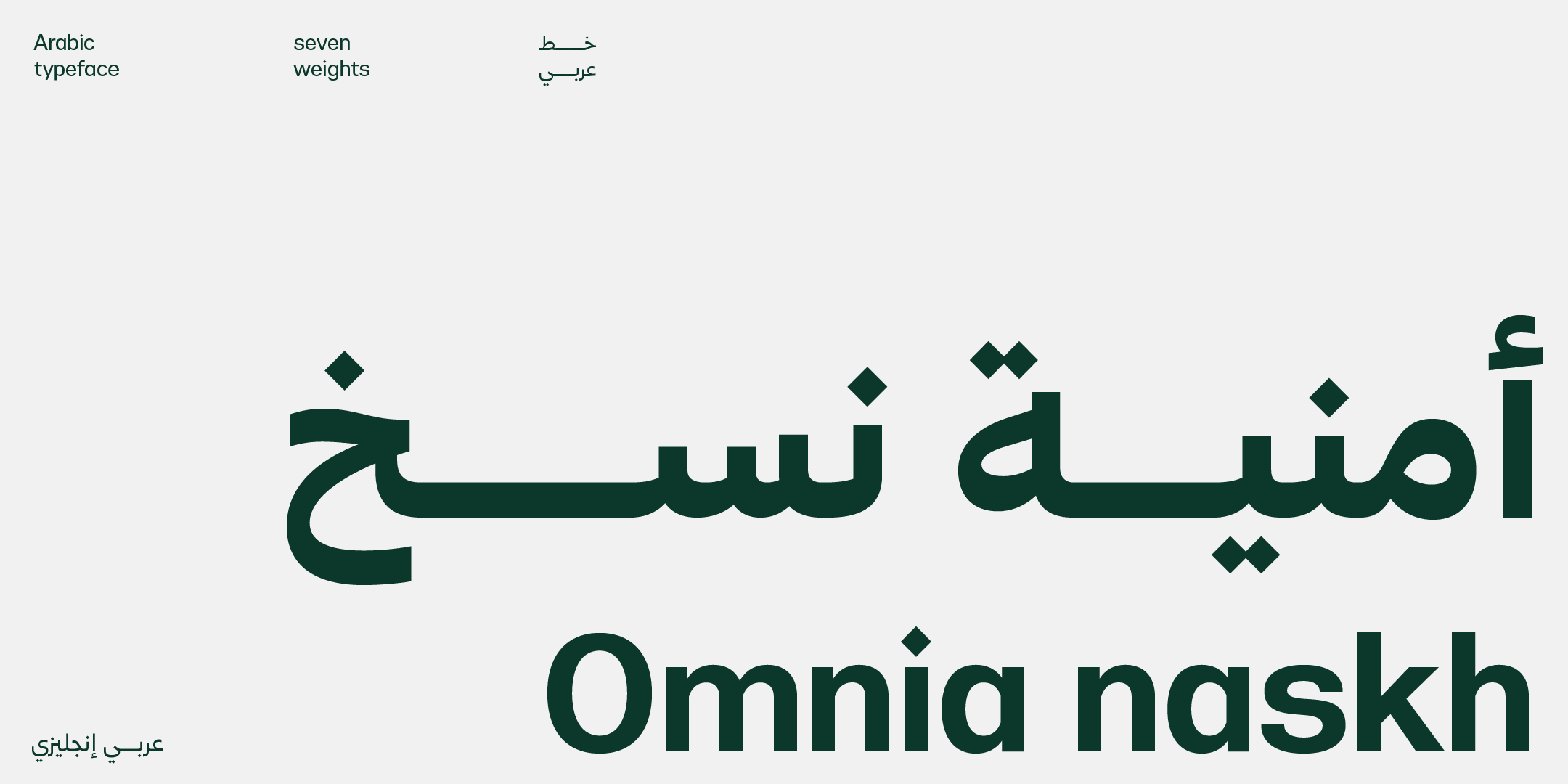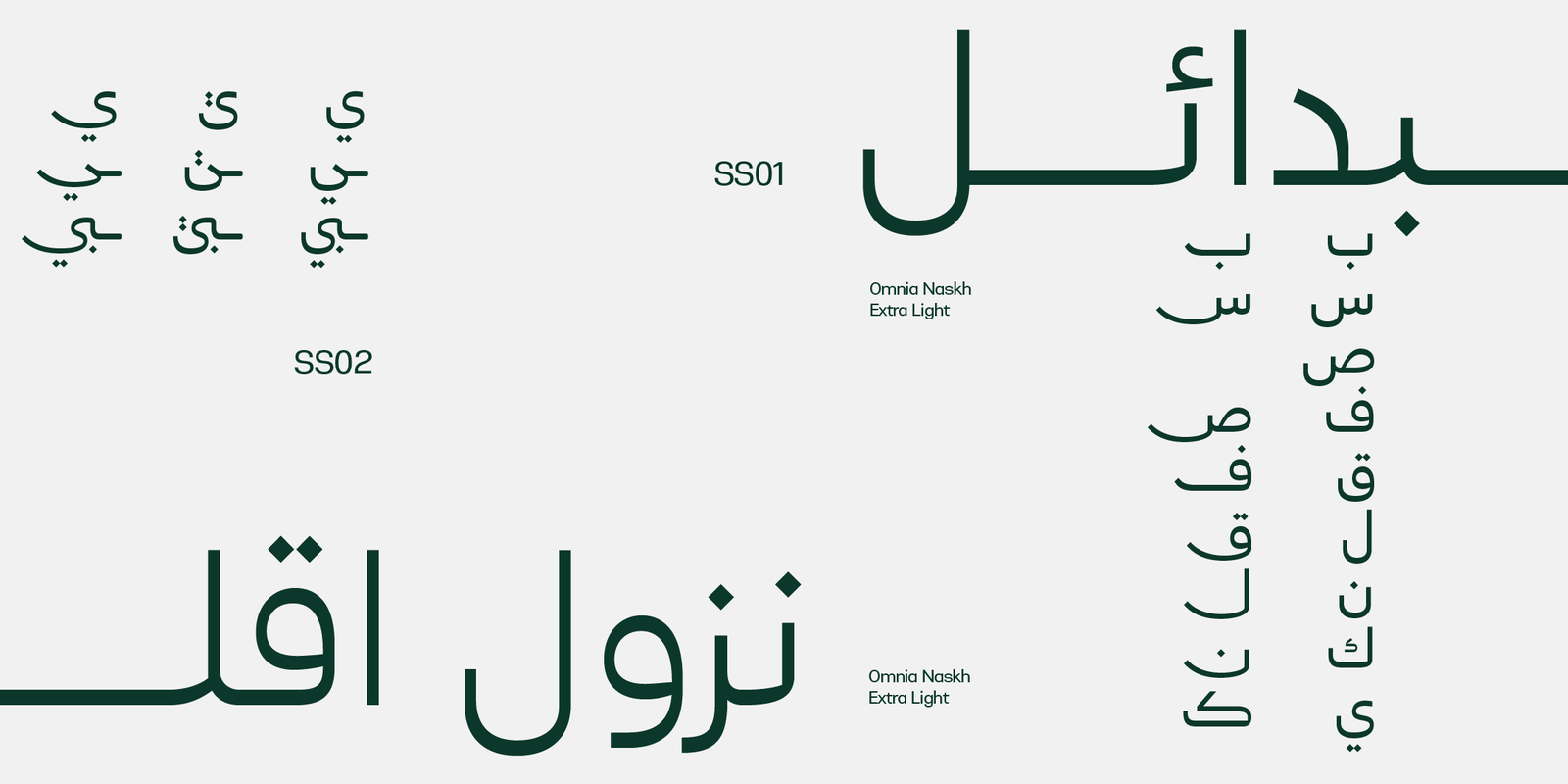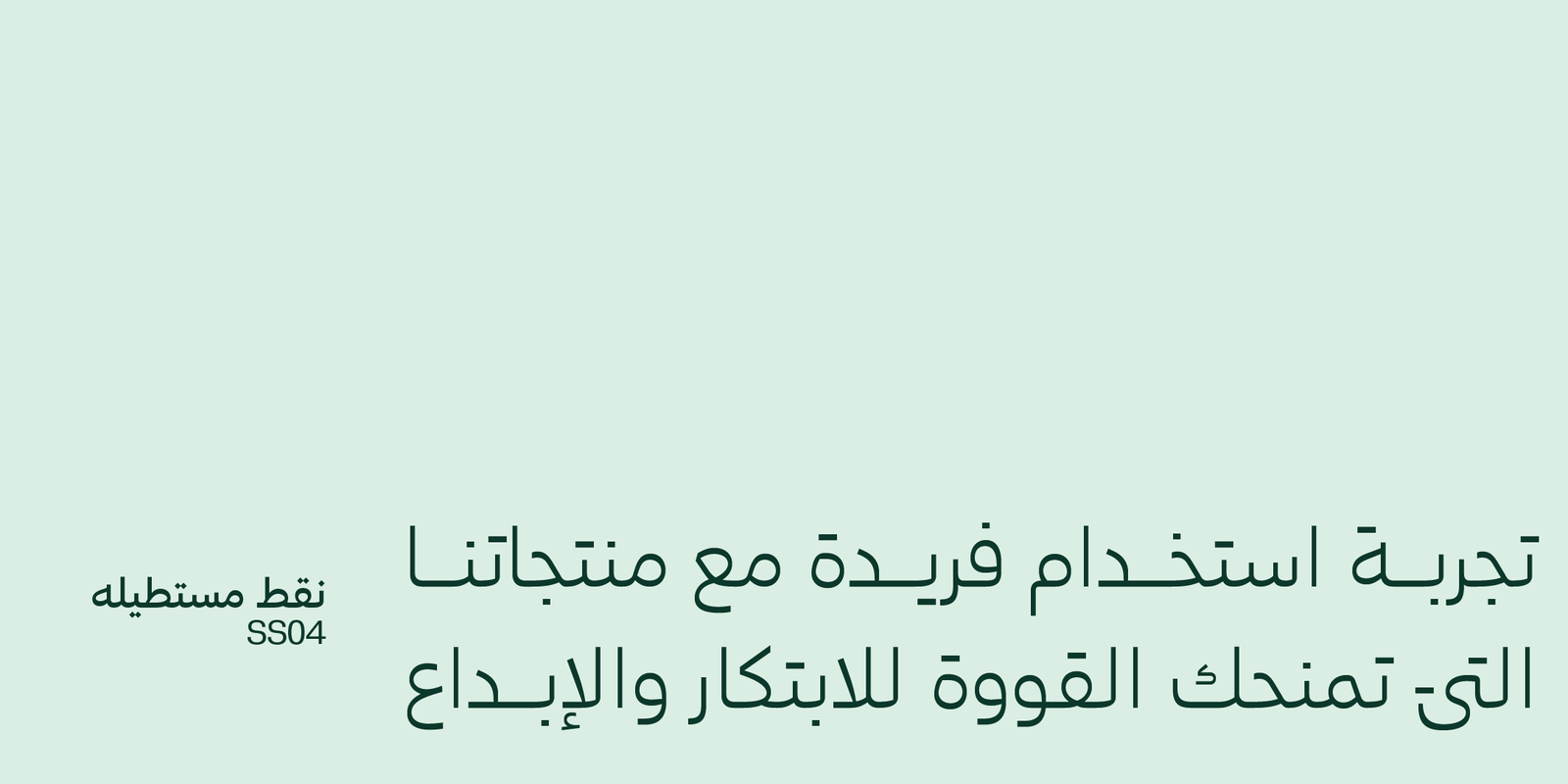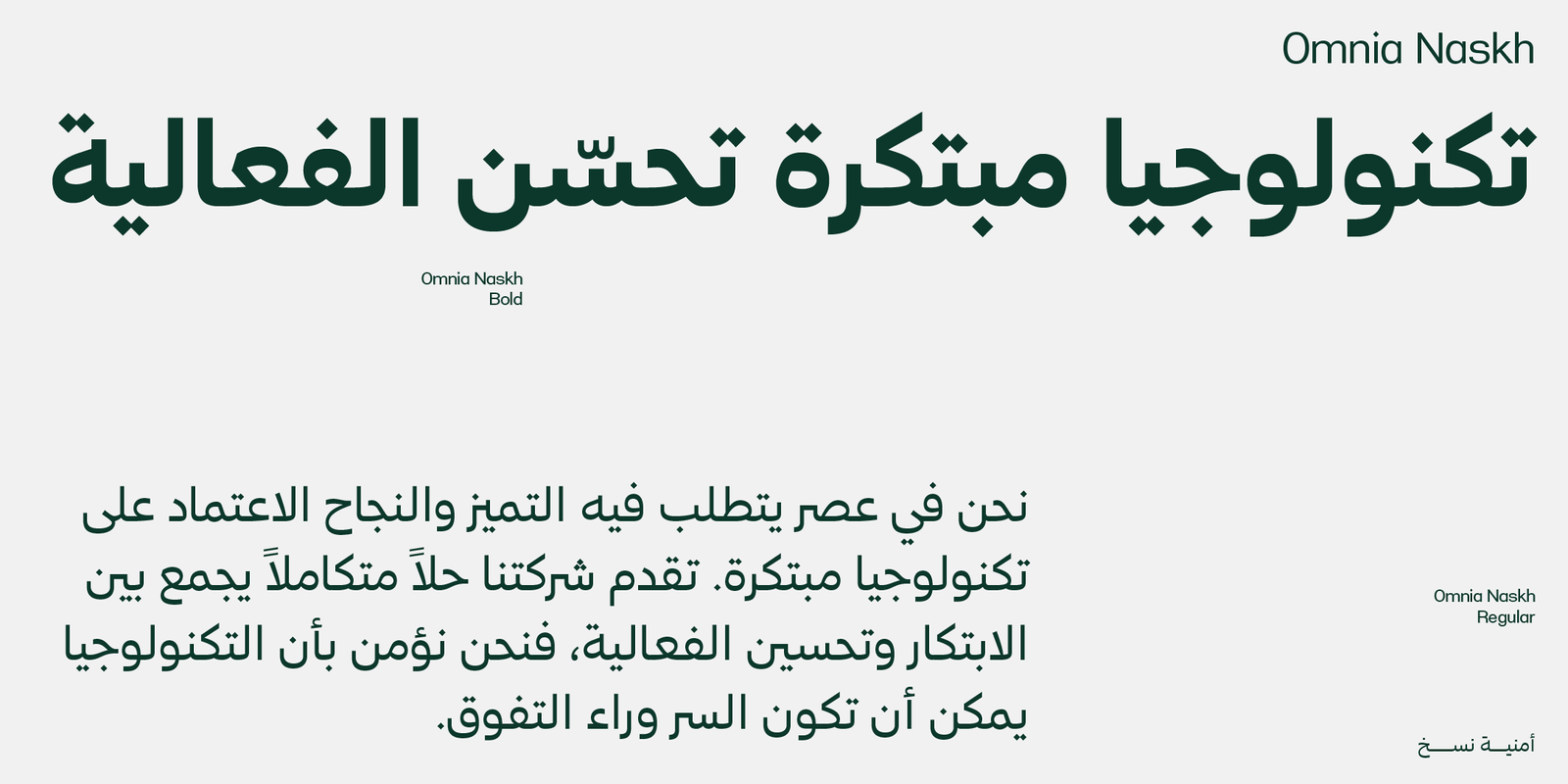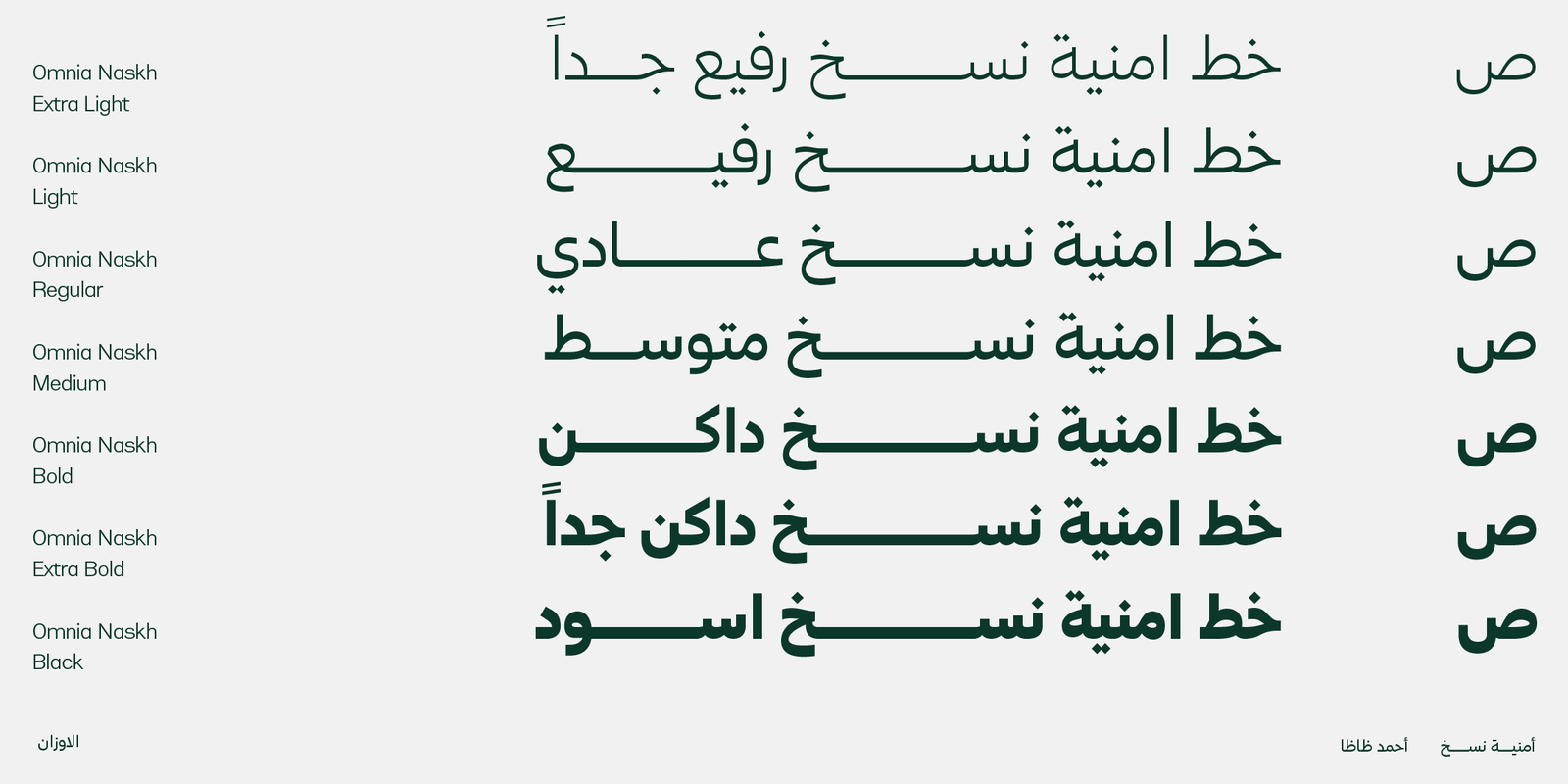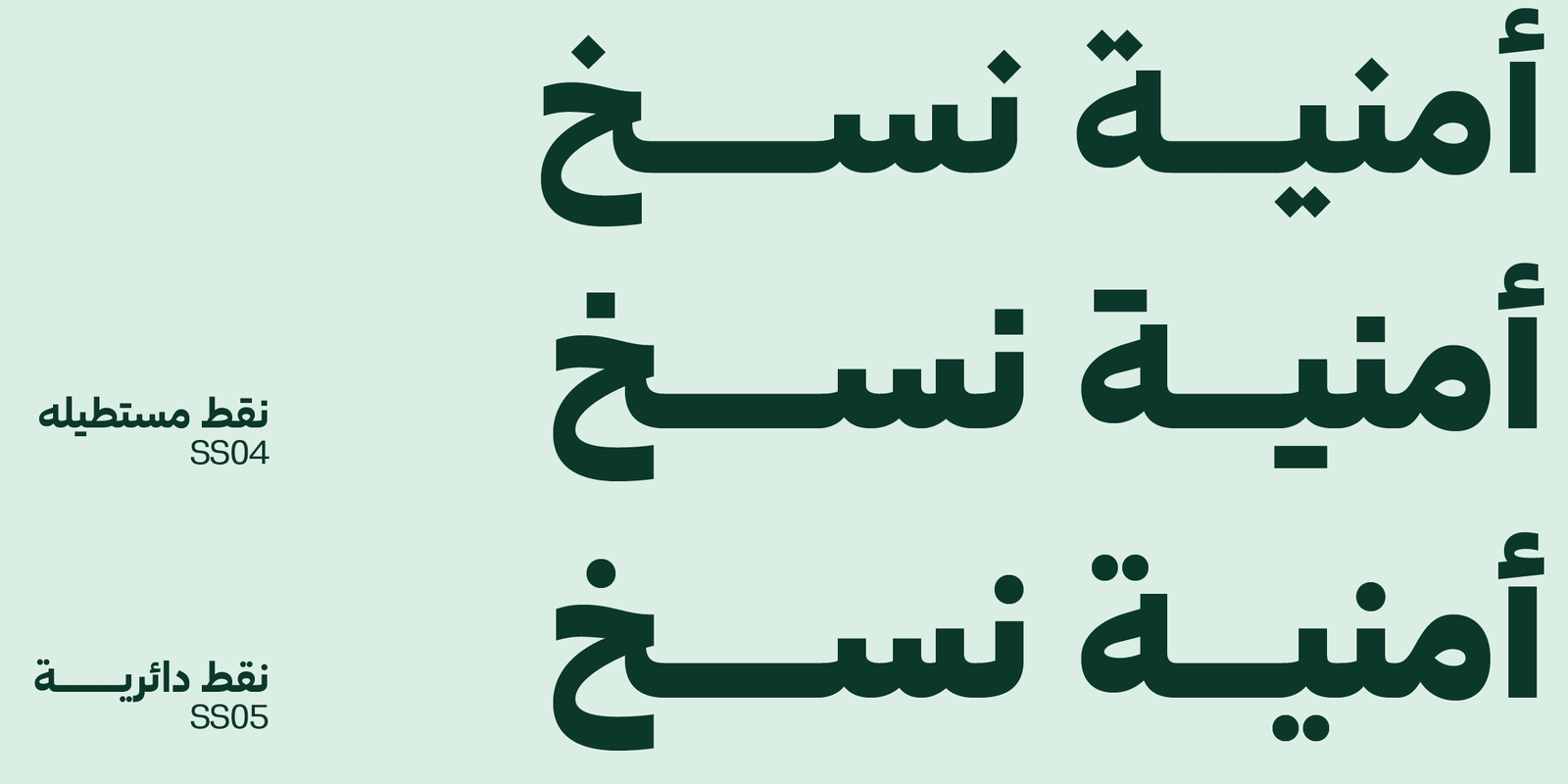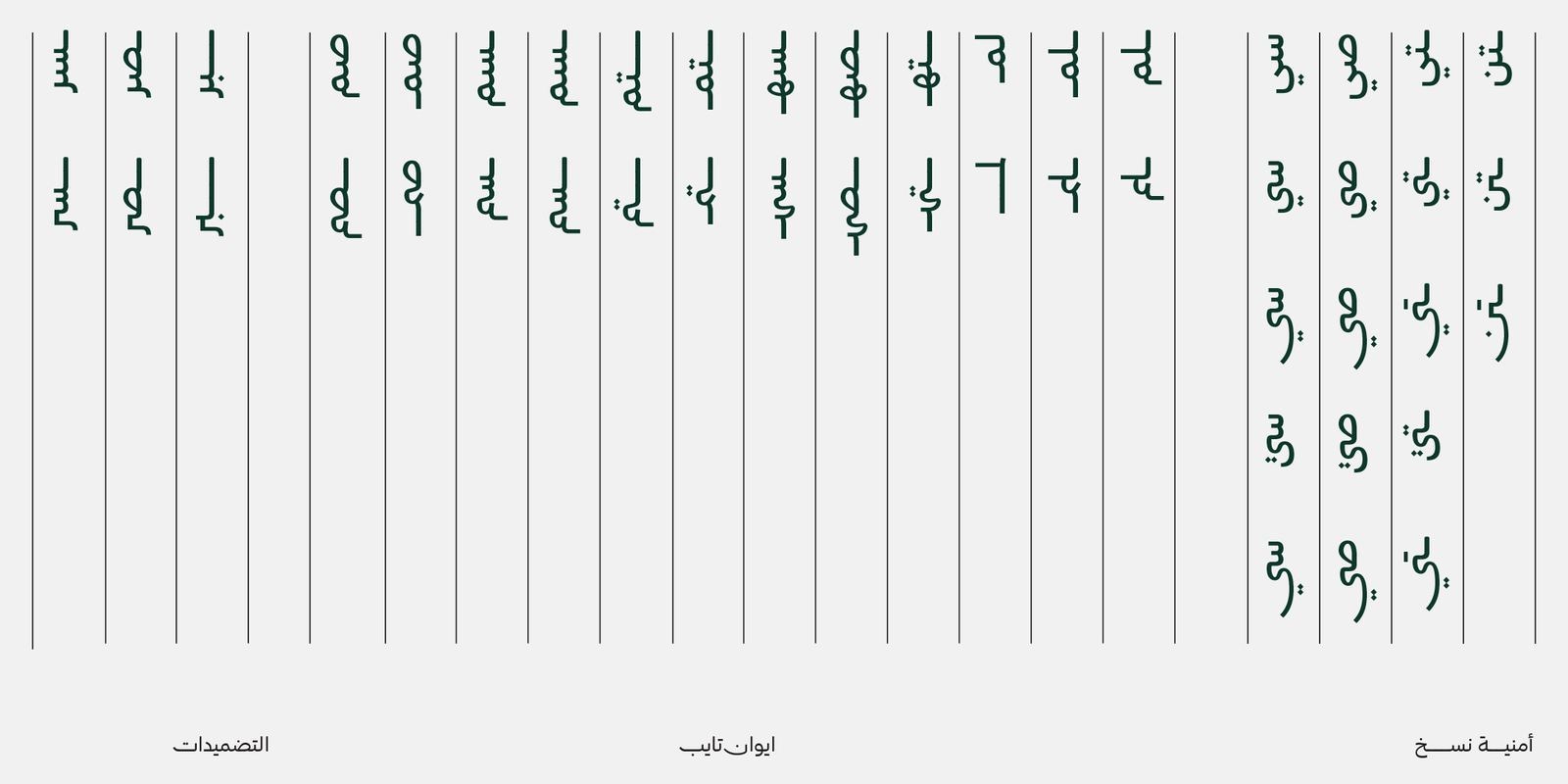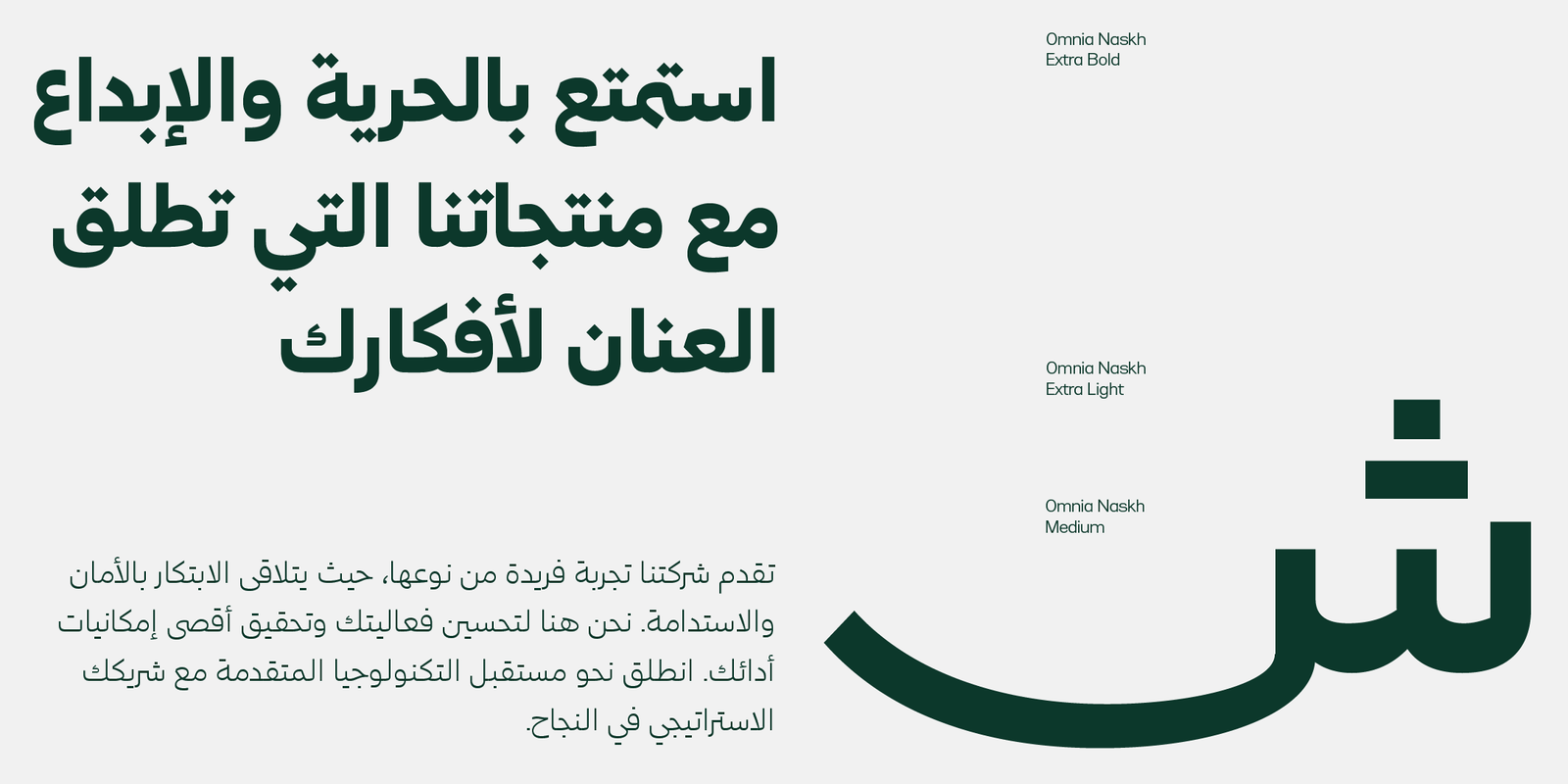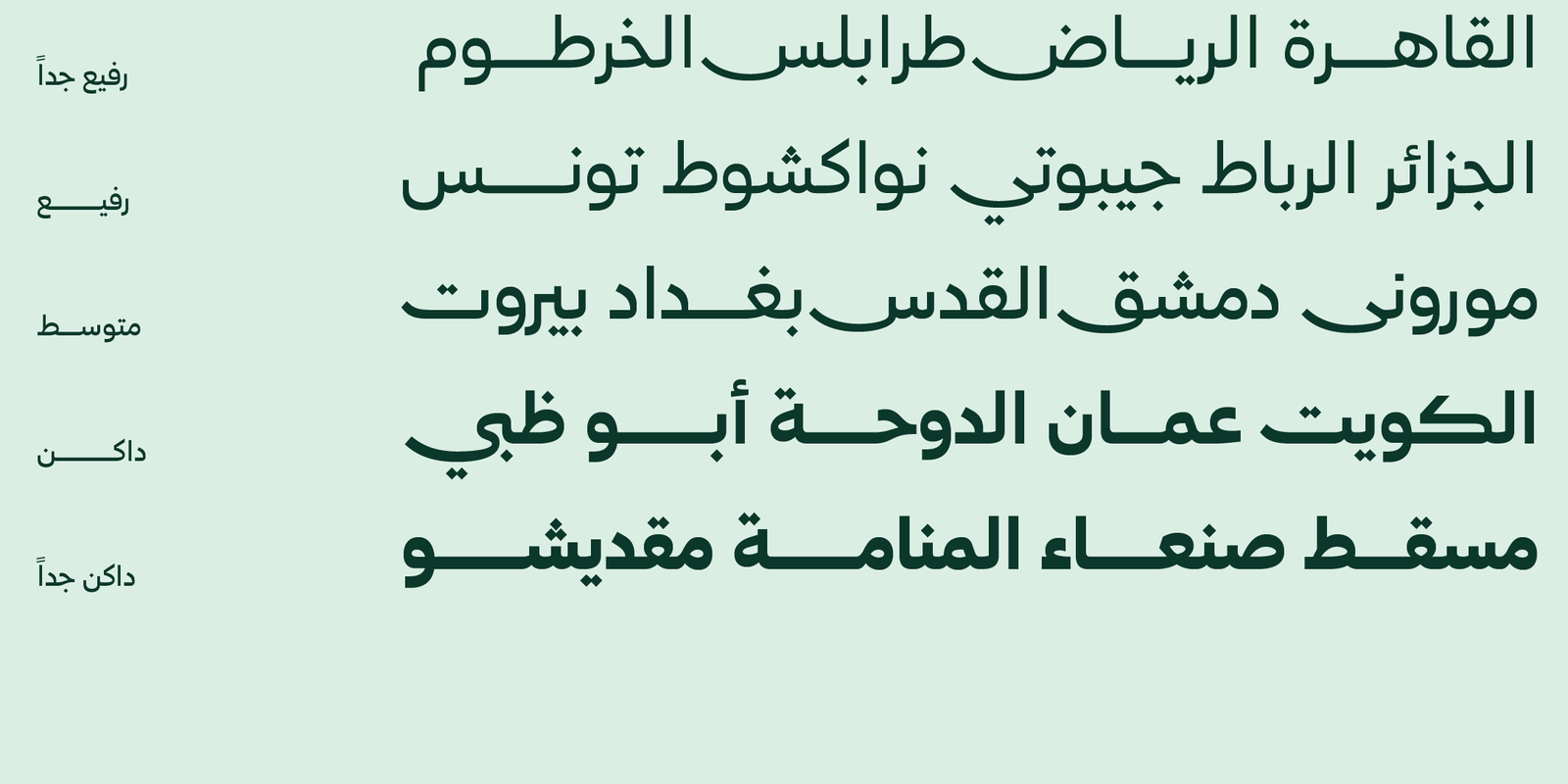
Omnia Naskh typeface – خط أمنية نسخ
Omnia Naskh typeface – خط أمنية نسخ : خط عربي نسخ حديث يجمع بين الجمال والبساطة
أمنية نسخ هو خط عربي نسخ حديث واصدار من خط أمنية ويتميز بالأنحناءات الجمالية التي تعكس دقة التفاصيل. تم تصميمه لتوفير تجربة كتابية سلسة وغنية بالتفاصيل.تبرز مزايا أمنية نسخ بفضل وجود الحروف المركبة التي تضفي على النصوص تفردًا وأصالة. تسمح الحروف المركبة للمصممين والكتاب بإنشاء نصوص أكثر تنوعًا وجمالًا، مما يعزز التعبير الإبداعي.يضفي استخدام الحروف البديلة والحروف المرسلة للكتابة لمسة شخصية وتنوعًا على النصوص. تسمح الحروف البديلة للمصممين باختيار الأحرف التي تناسب احتياجات التصميم الخاصة بهم، بينما تسمح الحروف المرسلة بإنشاء نصوص أكثر سلاسة وجمالًا.الانسياب الرشيق لحروف أمنية نسخ يعكس توازنًا متقنًا بين التصميم الفني والوظائف العملية. يتميز الخط بوضوح في التصاميم الاحترافية، مما يضمن قراءة سهلة وفهمًا واضحًا.باستخدام النقاط البديلة بشكل حساس، يمكن تخصيص أمنية نسخ بدقة. تسمح هذه الميزة للمصممين بإنشاء نصوص أكثر تعبيرًا وحيوية، مما يسهم في تحسين جودة التصميم.يظهر أمنية نسخ بأنه خيار احترافي ينطوي على توازن رائع بين التصميم الدقيق والتعبير الفني. يجمع الخط بين الجمال والبساطة في تجربة كتابية فريدة وغنية بالتفاصيل.
اللغات: عربي انجليزي
الاوزان : سبعة أوزان